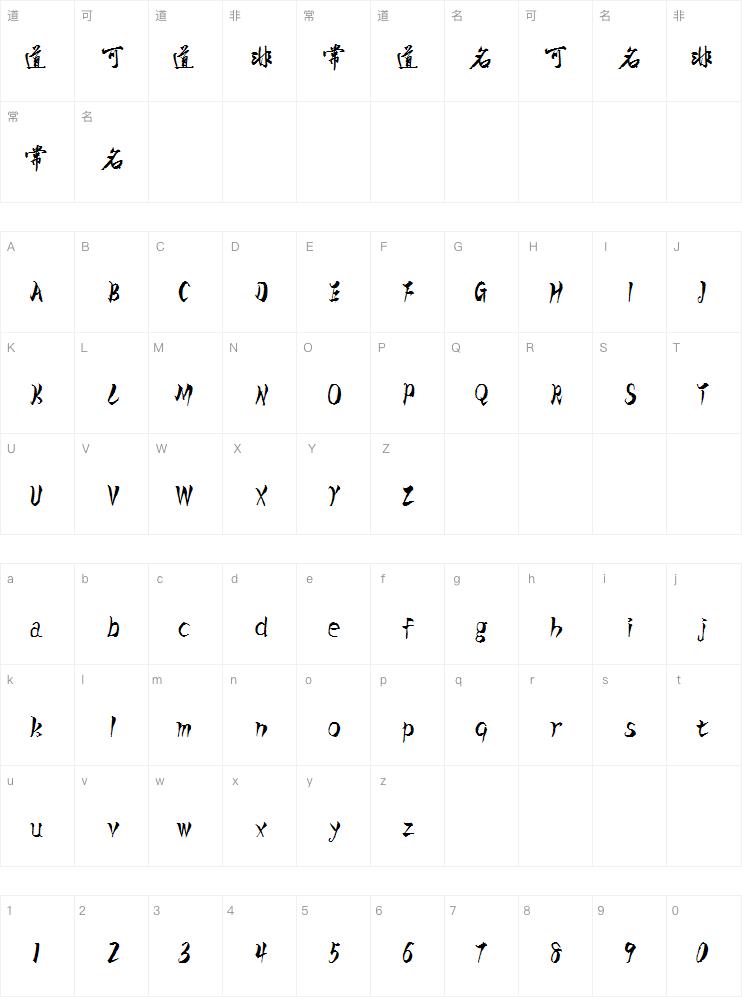
文徵明(1470-1559),原名壁,字征明。四十二岁起以字行,更字征仲。因先世衡山人,故号衡山居士,世称“文衡山”,明代画家、书法家、文学家。 文徵明的书画造诣极为全面,诗、文、书、画无一不精,人称是“四绝”的全才。在画史上与沈周、唐寅、仇英合称“吴门四家”。文徵明书法初师李应祯,后广泛学习前代名迹,篆、隶、楷、行、草各有造诣。尤擅长行。 汉标高清文徵明大字行书,作者运用现代造字技术,搜集古代文徵明行书真迹,历时5年经过多次研究文徵明笔画走势,结合文献资料主抓文徵明行书的韵律感,如音符轻弹悠扬,生动流畅。笔画流畅飞扬,结体左紧右松,开合对比强烈,进一步强化了动感。汉标高清文徵明大字行书字库的出现,让更多书法爱好者能够通过电脑打字使用,真正感受到名家书法之美。并且也可以在各种场景下应用。完美展示古代真迹书法本质,充分体现了笔锋之美。体现出一种随性和灵秀。总字数6763个。 汉标高清文徵明大字行书整套字体有如一气呵成,笔锋的立体感强烈,行笔迅捷华丽,其个性浪漫洒脱,适用于现代诗歌、短文的排版,以及文化、商业类品牌的广告语设计。